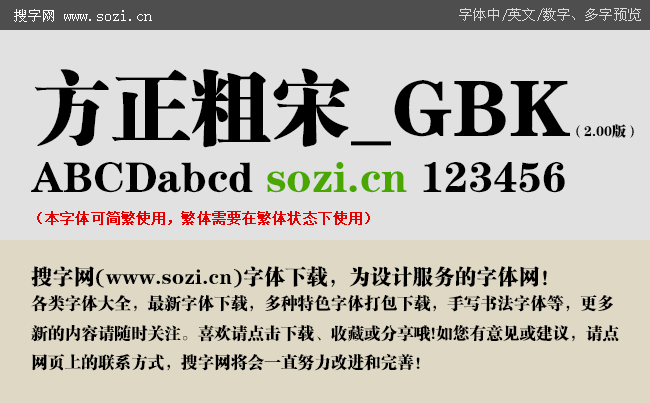
方正粗宋_GBK
搜字網(wǎng)提供一款方正粗宋_GBK中文字體下載,方正粗宋是一款非常美觀醒目的中文字體,適合在正式的場(chǎng)合來(lái)進(jìn)行使用,GBK編碼收字更全,適合應(yīng)用于廣告設(shè)計(jì)、名片設(shè)計(jì)、包裝印刷、產(chǎn)品設(shè)計(jì)等應(yīng)用。